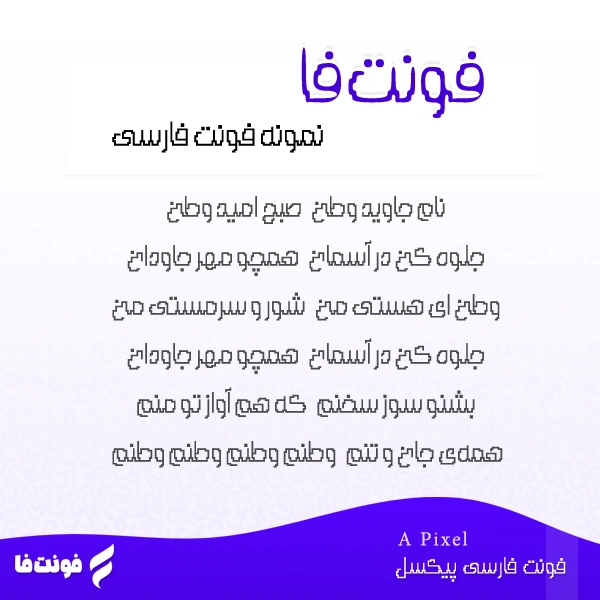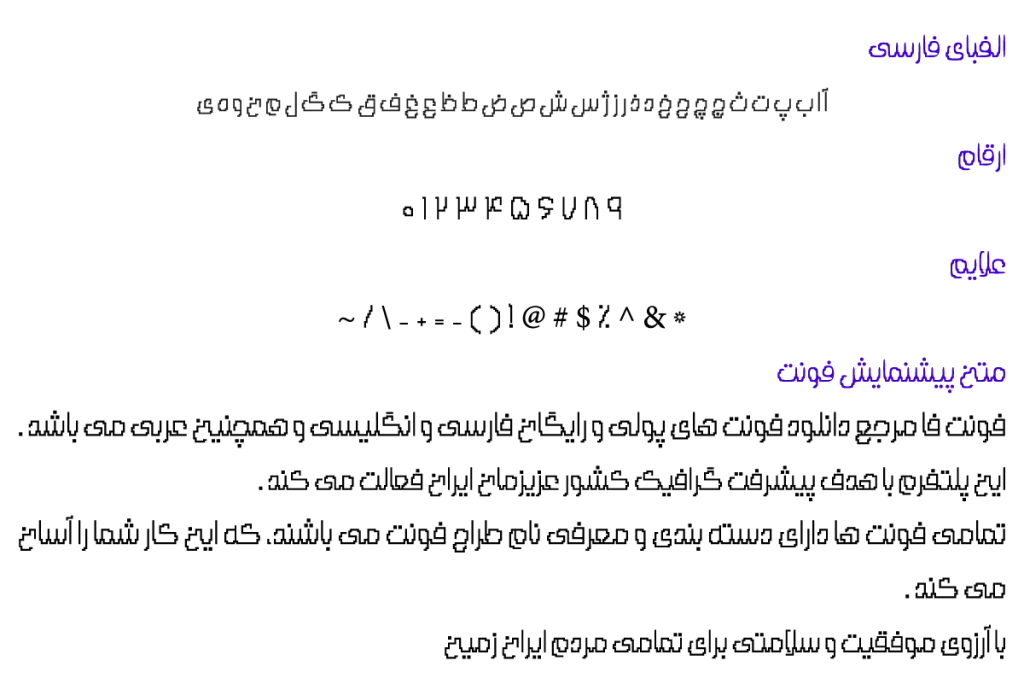
فونت فارسی پیکسل – A Pixel
سال ساخت فونت: 1393
طراح فونت: مجتبی کیا نوع فونت: فونت پیکسلی
توضیحات و معرفی فونت پیکسل
فونت فارسی پیکسل ( A Pixel ) از مجموعه فونت های آزاد می باشد، و نیز نوع فونت پیکسلی می باشد.
فونت خوشگل مربوط توسط مجتبی کیا در سال 1393 طراحی و ساخته شده است.
در عکس زیر، پیش نمایشی از این تایپ فیس را می بینید که با آن شعری کهن درباره ایران نوشته شده است.